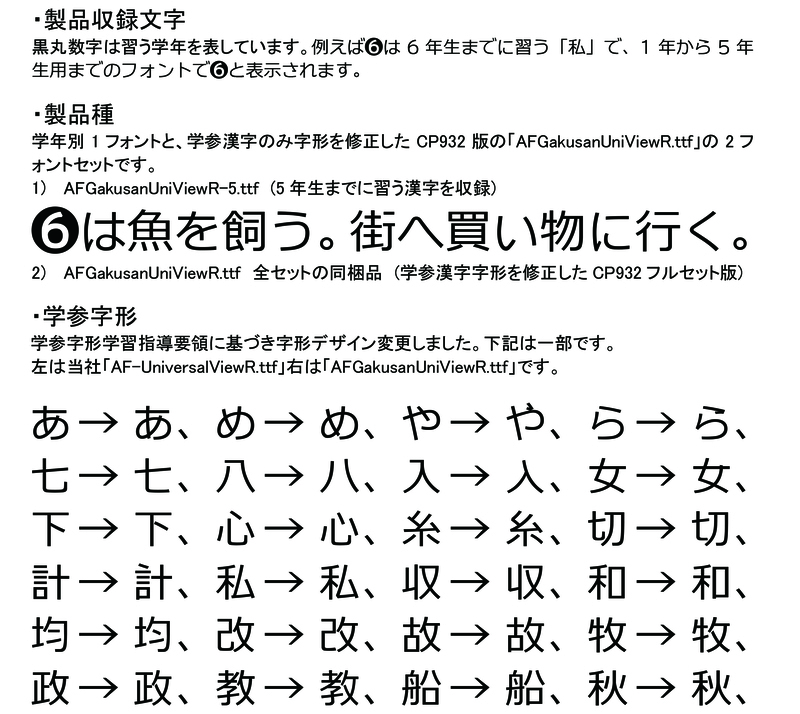
可読性を重視したユニバーサルビューのレギュラーをベースに文部科学省学習指導要領の字形を再現、他に類を見ない学年別学参フォントをご案内します。ドリル等教材用はもちろん児童を対象とした配布資料作成に最適です。その対象学年までに習う文字を収録したフォントと学参漢字のみ字形を修正したCP932フルセット版の2書体セットです。
学参 小学5年生用R